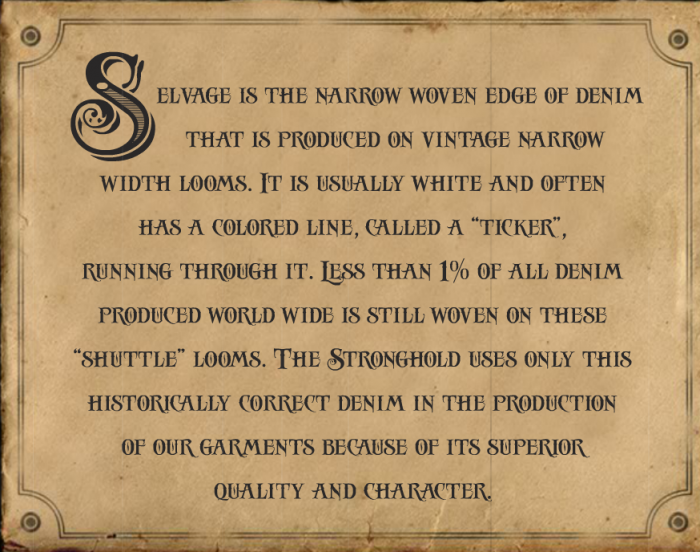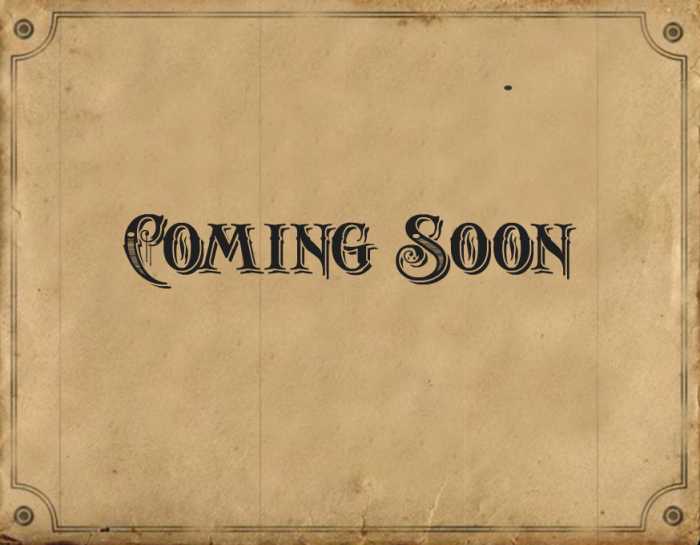
Suche verzweifelt diese "Western Schrift"
Nun zu meinem Problem. Ich suche verzweifelt nach einer bestimmten Schrift die ich nur auf Bildern habe. 2 Tagen durchstöbere ich verschiedenste Datenbanken ohne Erfolg.
Hat jemand von Euch die Schrift schon einmal gesehen oder hat einen guten Tipp für mich?